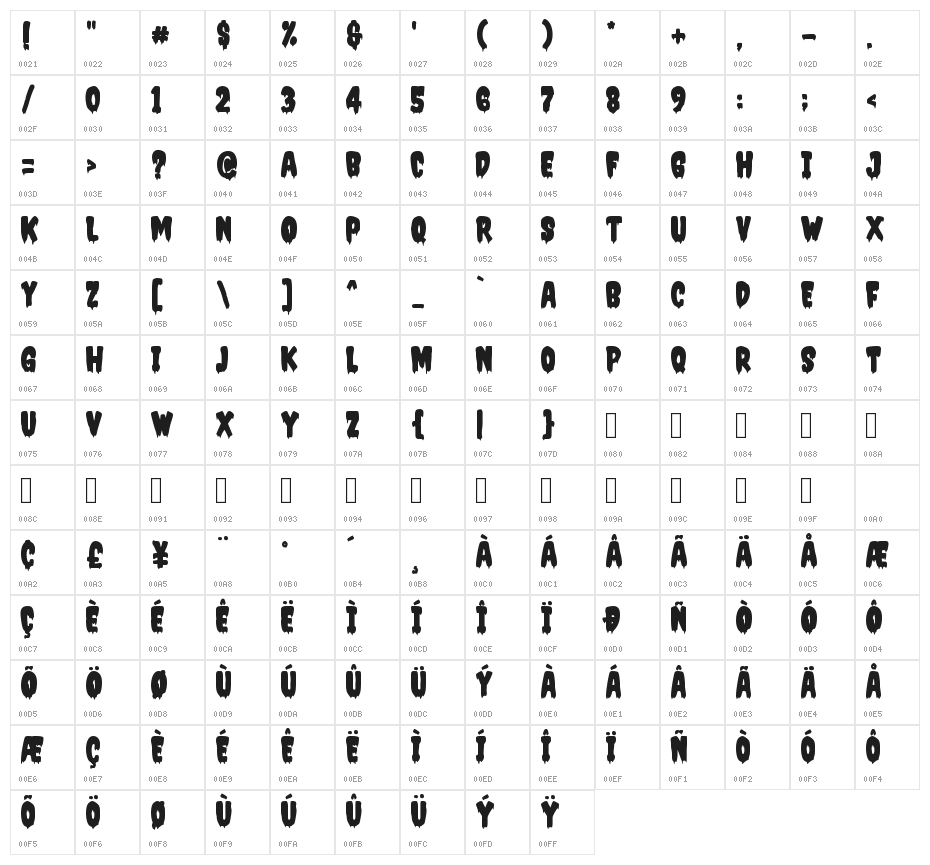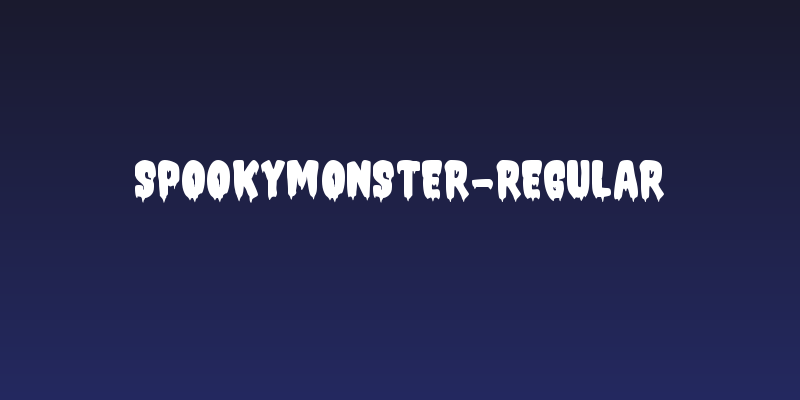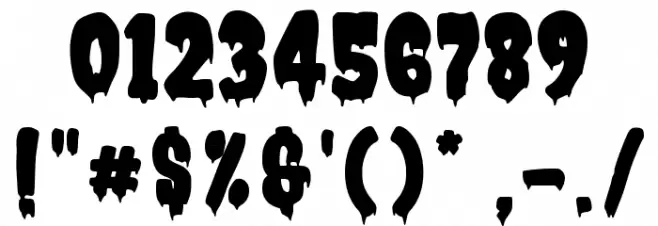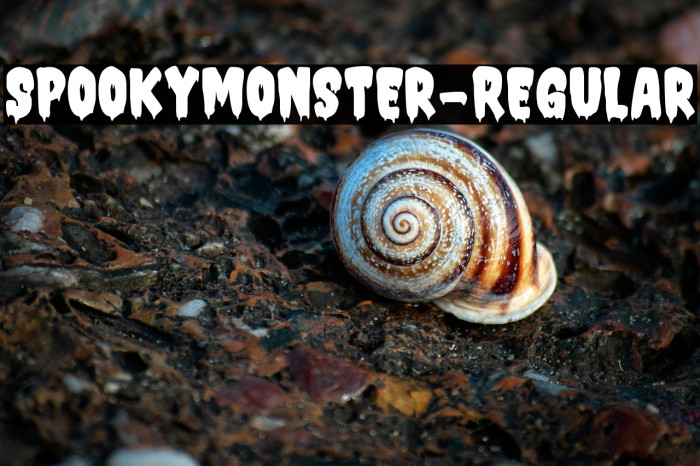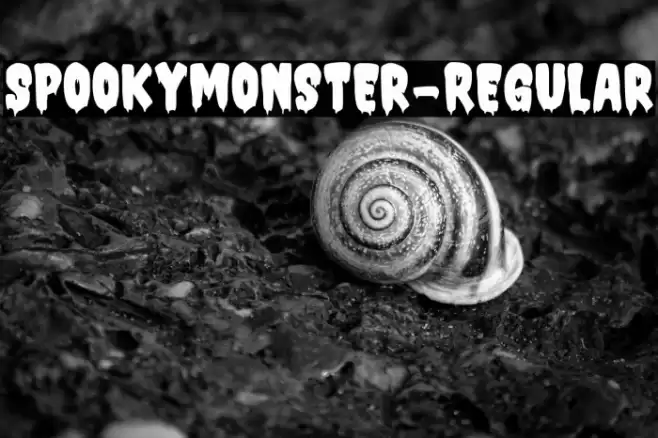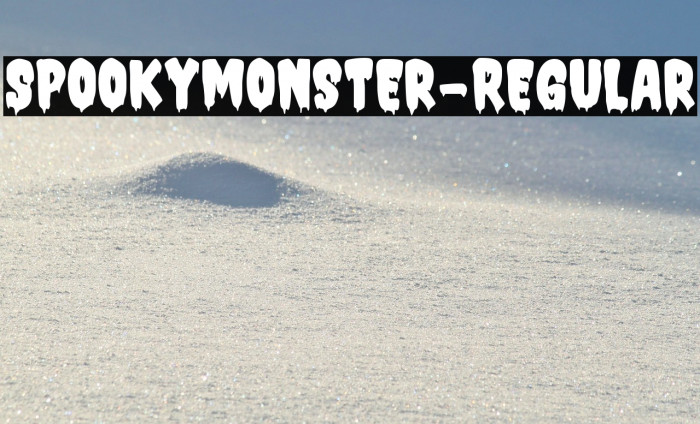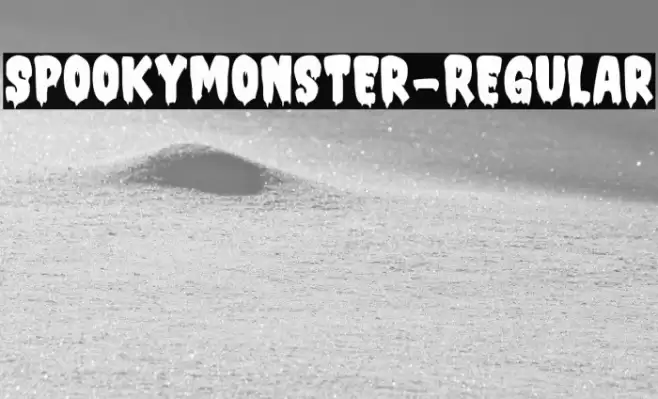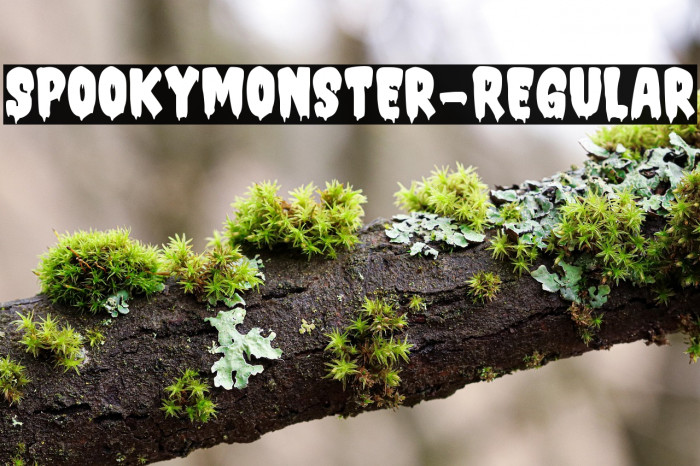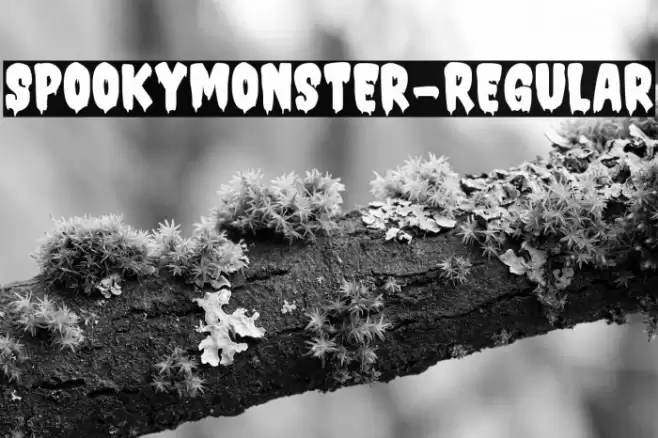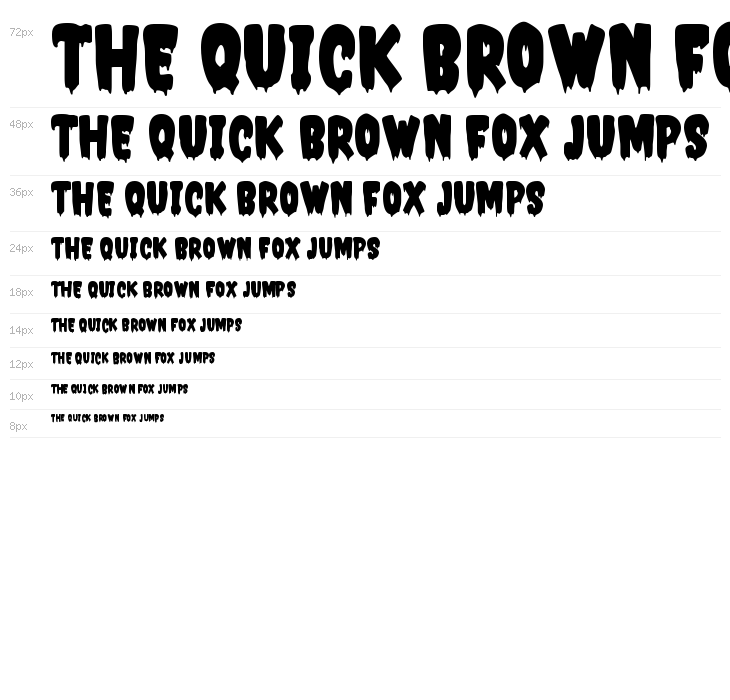
SpookyMonster-Regular Font
| Schriften Familie | Spooky Monster |
| Kategorien | Halloween |
| Anwendungsfall | Headlines, Posters, Invitations |
| Vorgeschlagene Projekte | Halloween invitations, horror movie posters, themed party decorations, spooky event flyers. |